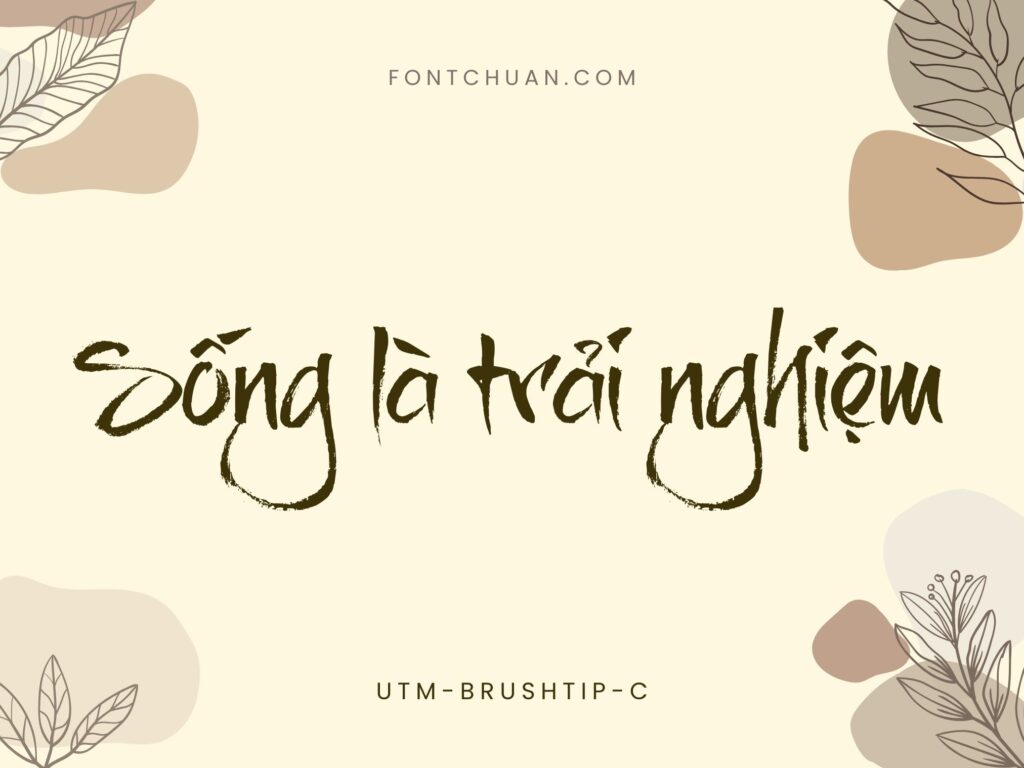
Font UTM Brushtip-C Việt Hóa
UTM Brushtip-C là phiên bản Việt hóa của font chữ Brushtip-C, một Font Script mang phong cách viết tay với các nét cọ mạnh mẽ và tự nhiên. Font này được thiết kế bởi JOEBOB graphics và nổi bật với các ký tự có đường nét thô ráp, tạo cảm giác năng động và phóng khoáng. Phiên bản Việt hóa đã được thực hiện bởi Unicode Thiên Minh, hỗ trợ đầy đủ tiếng Việt cùng hơn 100 ngôn ngữ khác. Đây là một trong những font được cộng đồng thiết kế sưu tầm và chọn lọc nhằm đáp ứng nhu cầu đa dạng trong thiết kế.
UTM Brushtip-C có cấu trúc chữ với các nét cọ dày – mỏng đan xen, mang đậm tinh thần tự do của Font Handwritten, giúp thiết kế trở nên tự nhiên và sinh động hơn. Font này phù hợp cho các ứng dụng như thiết kế tiêu đề, logo, bao bì sản phẩm và các ấn phẩm in ấn yêu cầu sự cá tính, nghệ thuật và gần gũi. Ngoài ra, Font chữ spa cũng có thể ứng dụng hiệu quả trong các thương hiệu làm đẹp, chăm sóc sức khỏe hoặc spa cao cấp nhờ cảm giác mềm mại và thư thái mà UTM Brushtip-C mang lại.